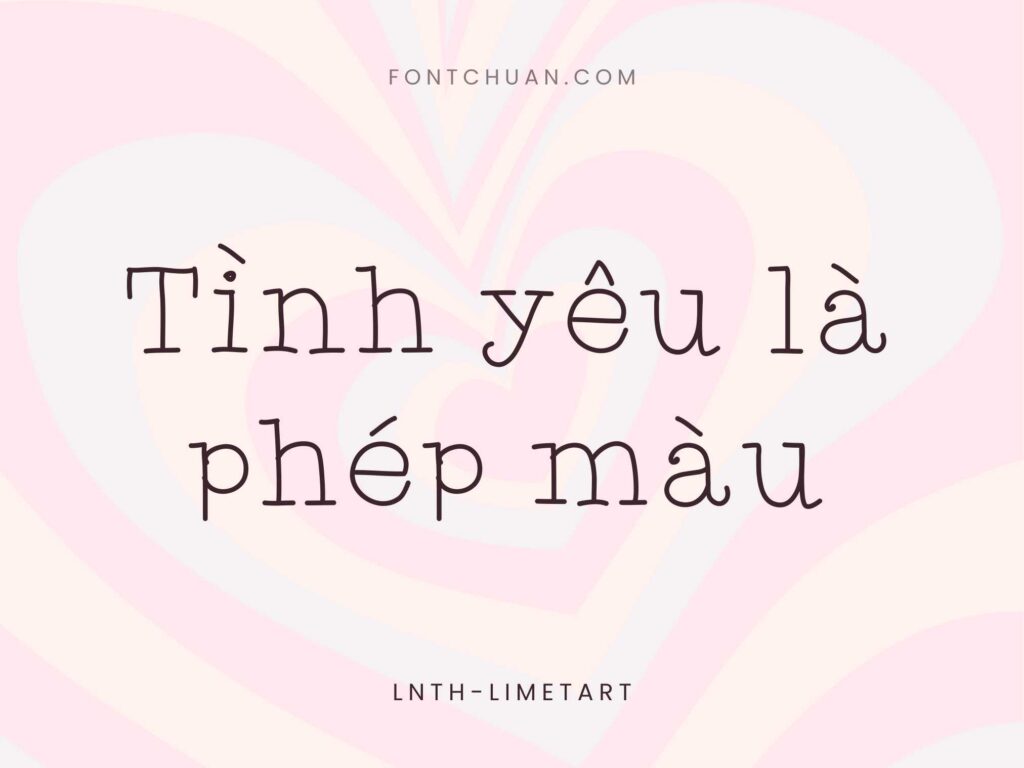
Font LNTH Limetart Việt Hóa
Font Limetart là một kiểu chữ viết tay hiện đại, mang phong cách tinh tế và sáng tạo. Với các đường nét mềm mại nhưng vẫn giữ được độ chắc chắn, Limetart mang lại cảm giác tự nhiên và thân thiện, rất thích hợp cho các thiết kế nghệ thuật, thương hiệu cá nhân hoặc các dự án liên quan đến phong cách trẻ trung, năng động
Phiên bản này đã được Việt hóa bởi LNTH, hỗ trợ đầy đủ tiếng Việt cùng hơn 50 ngôn ngữ khác, giúp người dùng dễ dàng ứng dụng trong thiết kế quốc tế. Font Limetart được các thành viên Font Chuẩn sưu tầm và đăng tải nhằm cung cấp một lựa chọn độc đáo cho những ai yêu thích kiểu chữ viết tay phá cách, đầy cảm hứng
Về đặc điểm thiết kế, Limetart có cấu trúc chữ tự do, các nét cong uyển chuyển kết hợp với độ dày vừa phải, tạo nên sự hài hòa trong thiết kế. Kiểu chữ này rất phù hợp để sử dụng trong typography nghệ thuật, thiết kế thương hiệu, bao bì sản phẩm hoặc các ấn phẩm quảng cáo sáng tạo
Font Limetart được ứng dụng rộng rãi trong các sự kiện như Valentine, thiệp mời hoặc các thiết kế cá nhân hóa. Nó phù hợp với nhiều ngành nghề như quảng cáo, spa, ẩm thực, giáo dục